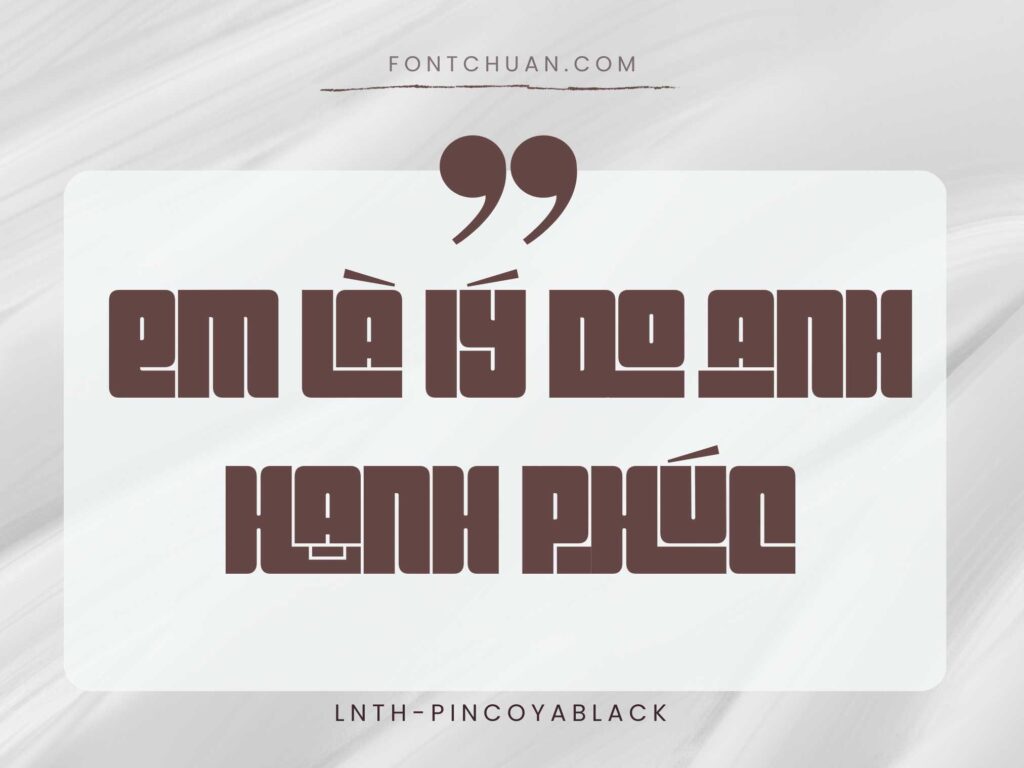
Font LNTH Pincoya Black Việt Hóa
Font Pincoya Black là một kiểu chữ mạnh mẽ, mang phong cách đậm chất đô thị và street art. Với thiết kế đậm, góc cạnh và đầy cá tính, font này phù hợp với các thiết kế quảng cáo, áp phích, tiêu đề lớn hoặc bất kỳ dự án nào cần sự nổi bật. Pincoya Black mang đến cảm giác mạnh mẽ, táo bạo, tạo nên điểm nhấn đặc biệt trong các thiết kế đồ họa sáng tạo
Phiên bản này đã được Việt hóa bởi LNTH, hỗ trợ đầy đủ tiếng Việt cùng hơn 50 ngôn ngữ khác, giúp người dùng dễ dàng ứng dụng trong thiết kế quốc tế. Font Pincoya Black được các thành viên Font Chuẩn sưu tầm và đăng tải nhằm cung cấp một sự lựa chọn đặc sắc dành cho những ai yêu thích phong cách typography hiện đại và cá tính
Về đặc điểm thiết kế, Pincoya Black có các nét chữ dày, chắc chắn với kết cấu hình khối vững vàng. Kiểu chữ này rất phù hợp để sử dụng trong thiết kế thương hiệu, banner, nhãn mác hoặc các ấn phẩm truyền thông hiện đại
Font Pincoya Black được ứng dụng rộng rãi trong các sự kiện như lễ hội, chiến dịch quảng bá hoặc các thiết kế street style. Nó phù hợp với nhiều ngành nghề như quảng cáo, bất động sản, công nghệ, giáo dục